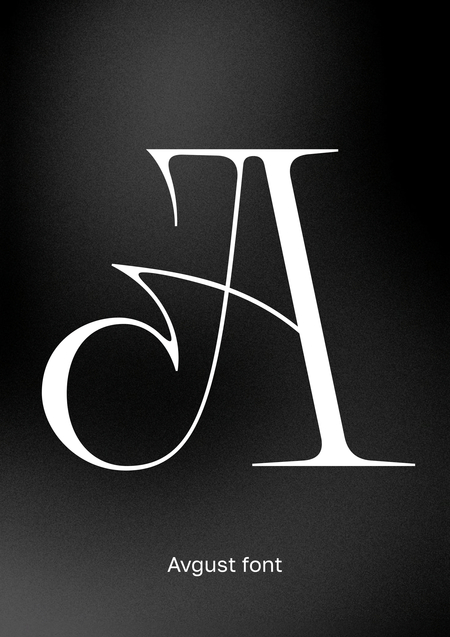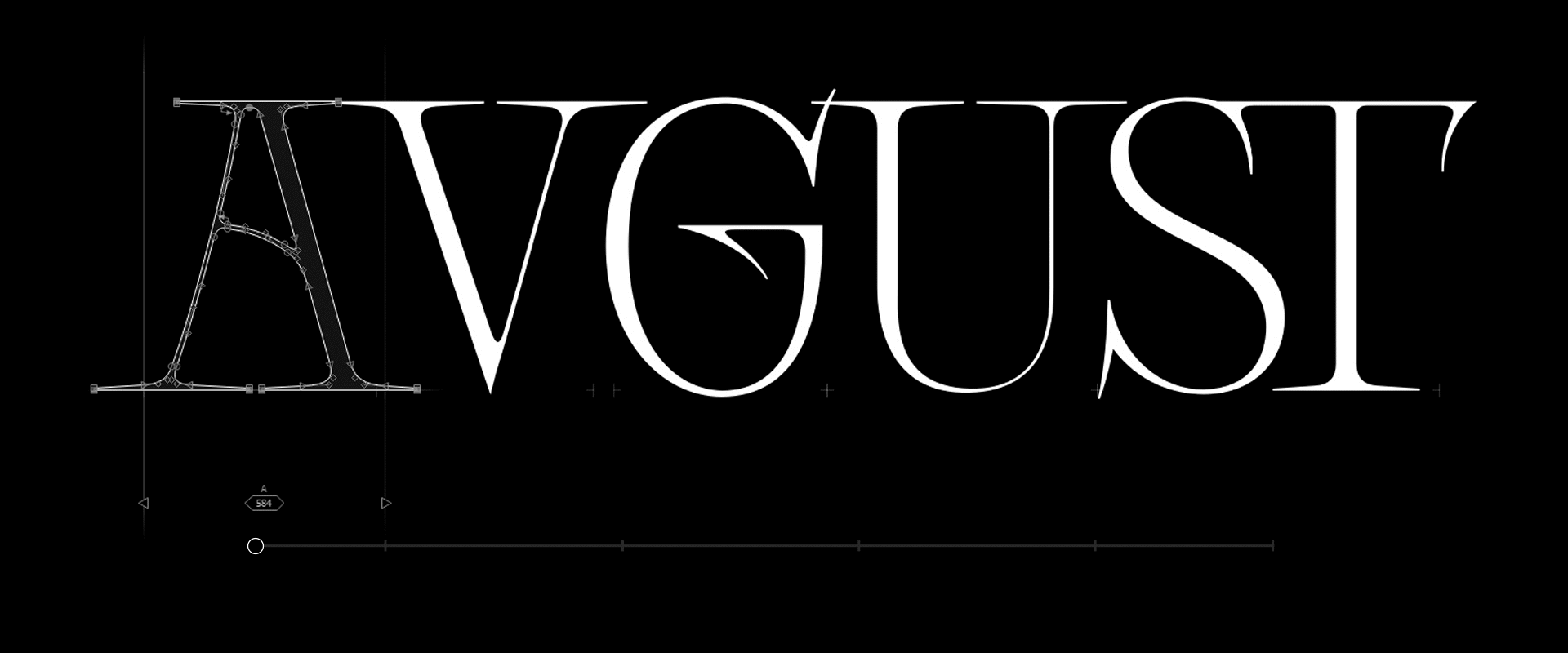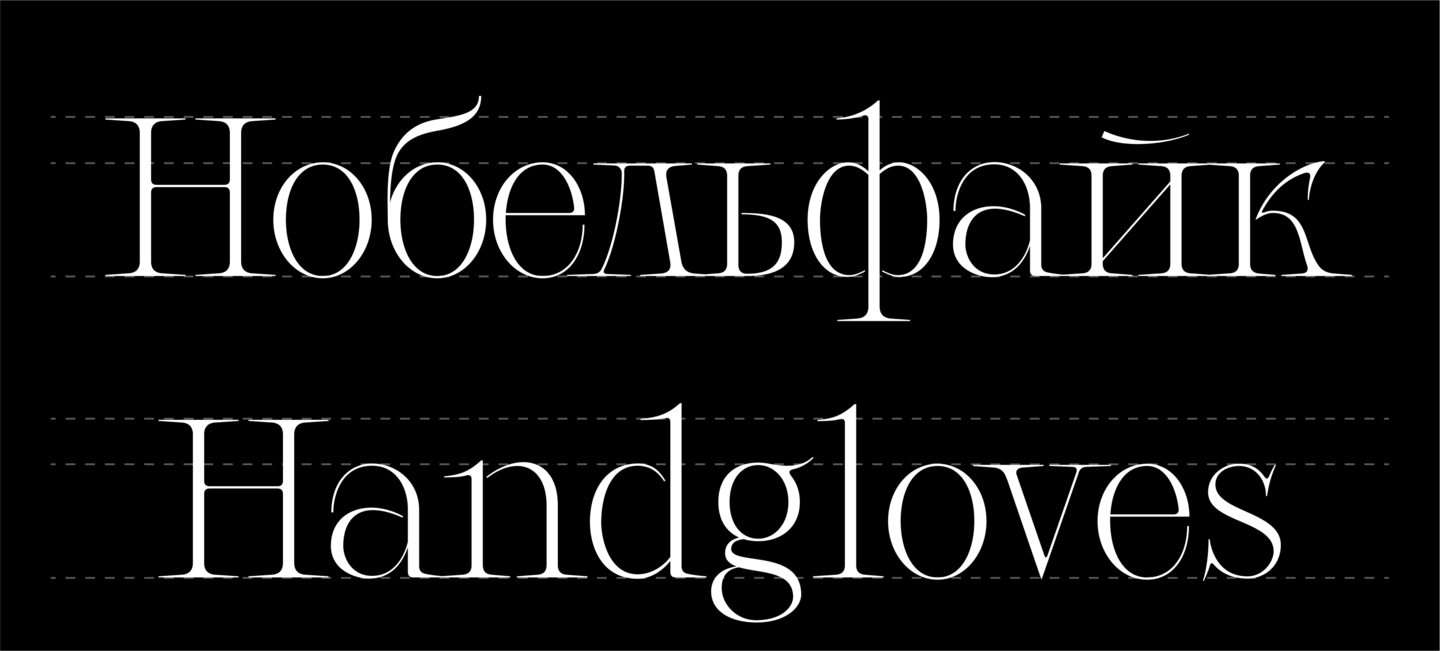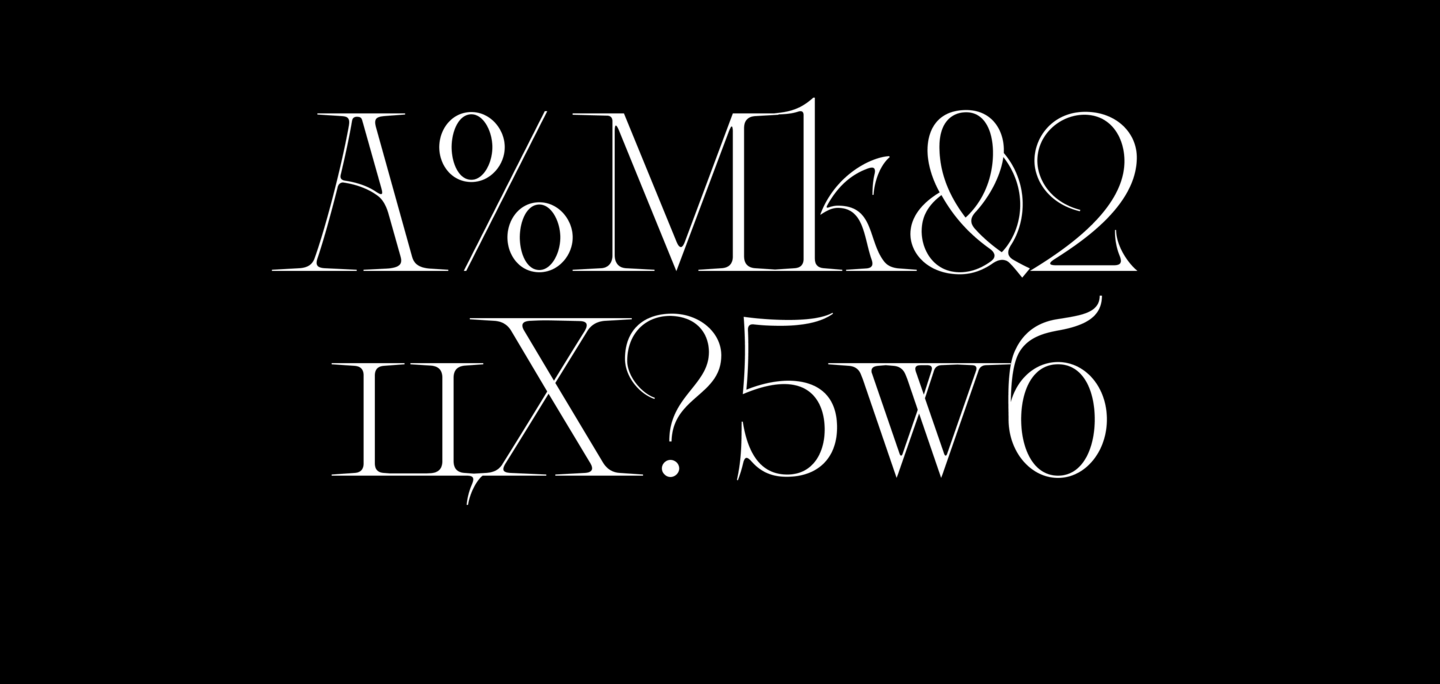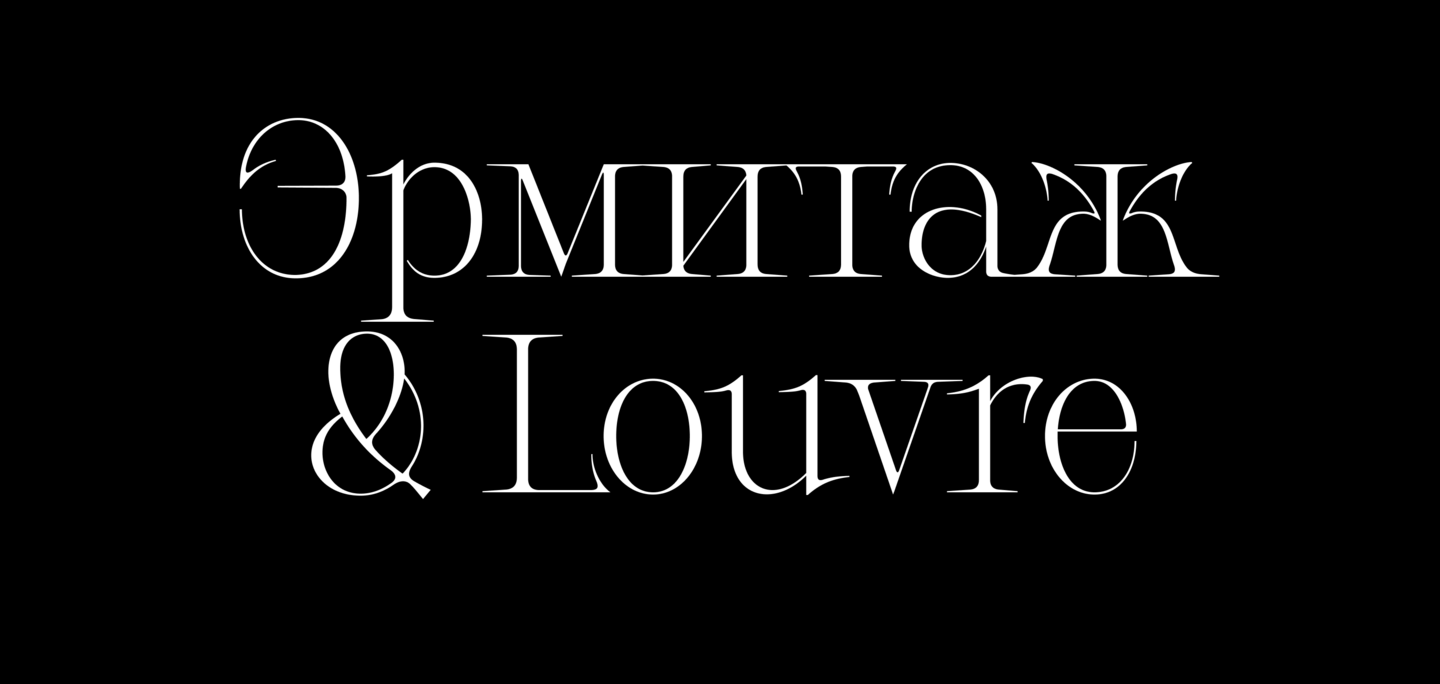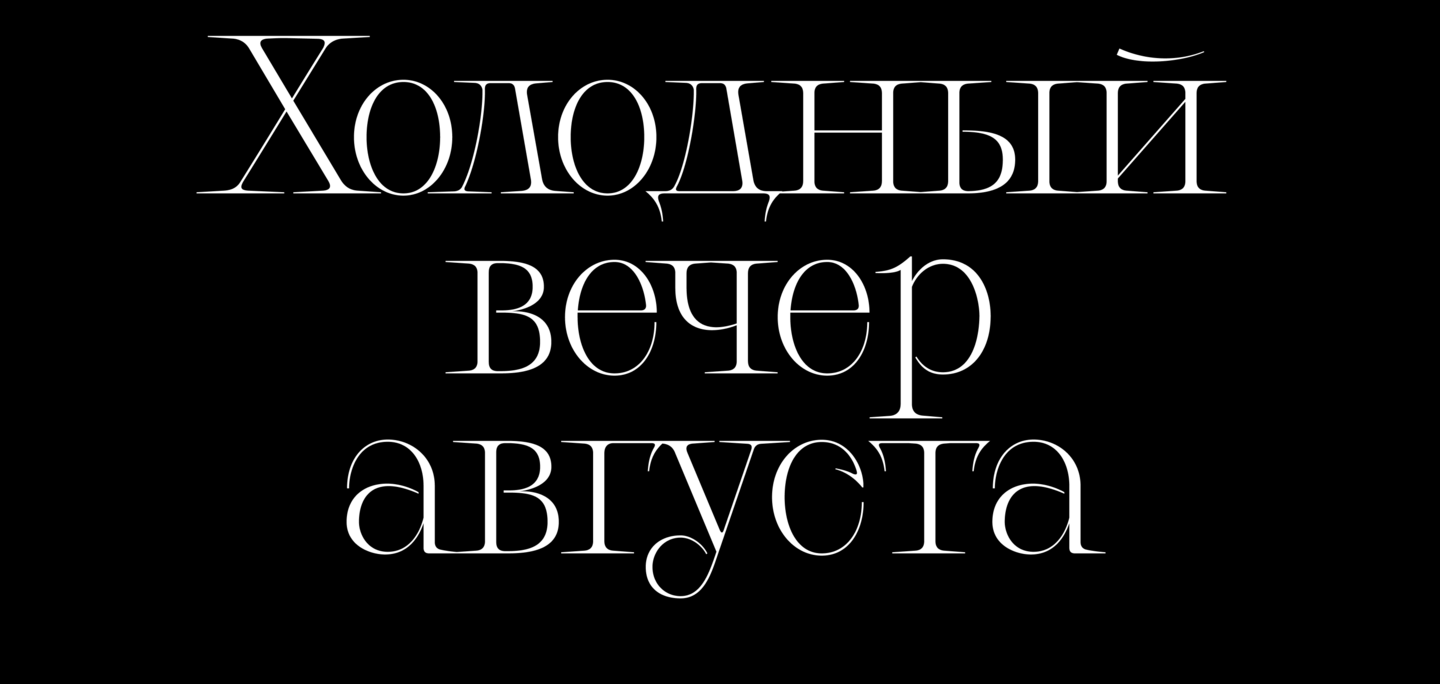
Шрифт Avgust
Акцидентная антиква с высоким контрастом. Первый релиз включает одно начертание.
Avgust был вдохновлен фотографией с решеткой окна, сделанной жарким днем в августе. И хотя затем он развивался и менялся, ее мотив можно проследить в ритме знаков и изяществе сгибов.
Полный набор включает латинский и кириллический алфавиты, альтернативные глифы, лигатуры, цифры и пунктуационные знаки.